昭和書体 雲外蒼天セット
「雲外蒼天セット」は、昭和書体の最高傑作と言われる「黄龍書体」と「般若書体」の2書体のセット。
雲外蒼天セット(黄龍書体+般若書体)書体見本
「黄龍書体」は、細身でありながら目立つ艶やかさを演出。
「般若書体」は、闘龍等より豪快さを抑えつつも鋭さを持った書体。
雲外蒼天セット(黄龍書体+般若書体)活用例
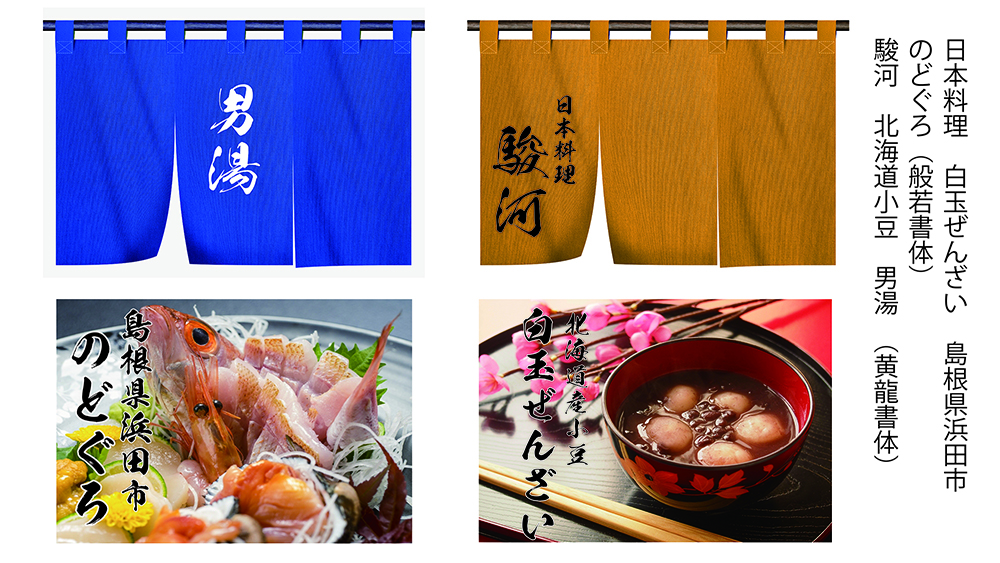
厳かな雰囲気を出したい時や、和の料理、店舗などワンポイントで使用する事で高級感を醸し出す。
昭和書体
昭和書体は、親子3代、50年続いた看板屋から2006年にコーエーサインワークスとしてフォント事業を開始。2013年現在の昭和書体に法人化。フォント業界では数少ない毛筆フォントに特化したフォントメーカーで、印刷しても直筆と遜色ない、かすれ、にじみを活かしたフォントが特長。
▼現在84歳、一人で40万字以上64書体をかき分けてきた。